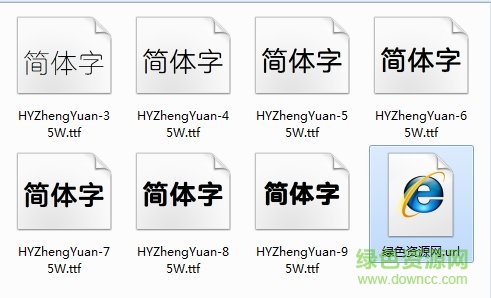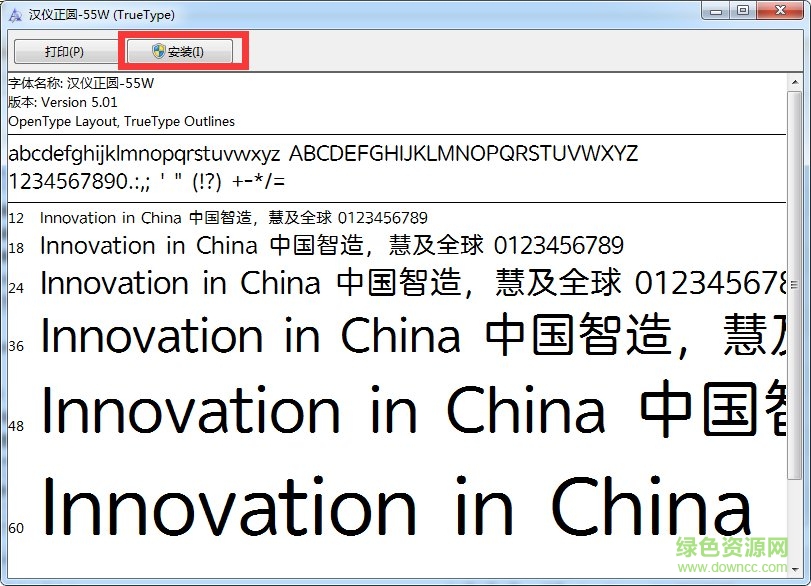
漢儀正圓字體打包文件里包含了7款免費的字體資源,有漢儀正圓45w、漢儀正圓55w等字體文件。這一個系列的字體外形規(guī)范、圓潤!在很多個設(shè)計領(lǐng)域都比較受歡迎!歡迎大家來綠色資源網(wǎng)下載使用。
漢儀正圓字體筆畫粗細一致,字體看起來很端莊大氣。無論是設(shè)計商標還是廣告都是個不錯的選擇!